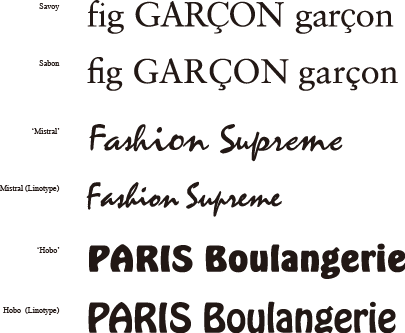
Q:「フォントの見方」について
1-1 フォントの良し悪しの見分け方
ソフトウェア等と同様、お金を払って使ってみないとフォントの実際の良し悪しはわかりませんが、何かのおまけについてくるフォント、格安フォントの中にはとんでもないものがあります。格安フォントの中から数書体みただけでもいくつか問題が見つかりました。
1列目サンプル参照:
「Savoy」という名前のついた Sabon のクローン書体です。
fi 合字がちゃんとしていないとか、小文字の g がやたらに扁平だとかは細かく見ると気になりますが、それよりも致命的なのはアクセント付き文字にまったく別のデザインの文字が混じっていることです。この場合は大文字 C の下にフランス語のシディラのアクセントが付いた文字は別の書体のデザインです。
今の時代、ロゴなどにフランス語の単語を使う可能性は十分あります。あなたがクライアントなら、こんなデザインに料金を払いますか? 怪しげな名前の格安フォントには、こんなとんでもない文字がどこに潜んでいるかわかりません。
ちなみに下はライノタイプから出ている由緒正しい Sabon のデジタル版です。
3列目サンプル参照:
堂々と「Mistral」という名前がついているのですが、オリジナルの活字書体に忠実なライノタイプ社の Mistral と比べると違いは歴然です。上の「Mistral」は本の付録についていました。字の形はいいかげんで、小文字のつながりがうまくいっていません。
5列目サンプル参照:
オリジナルの活字書体 Hobo は、小文字を混ぜて組んでも単語のデコボコが少なくなるような小文字 g や p などのディセンダーをベースラインに収めたり x ハイトを極端に高くしたりと工夫されていて、独特の雰囲気を持つアールヌーボー風の見出し用書体です。上が本の付録の「Hobo」です。小文字のディセンダーをベースラインに収めるというコンセプトは無視されていますし、大文字のスペーシングは良くありません。下がライノタイプの Hobo です。
フォントはちゃんとしたメーカーから買ったほうが結局は安くつくはずです。
1-2 吟味の仕方:フォント検索ツールを活用しよう
「テーマにあった雰囲気の書体」「適材適所の書体」を選ぶことは大事です。とくに欧米のデザイナーは自分の手持ちのフォントにテーマに合うものがないと、フォントメーカーに「こういう雰囲気のものがないか」と問い合わせをしてくるくらい神経を使います。
ライノタイプのホームページでは、ウェブサイトでの試し組みやグリフの一覧を見ることができます。とくにロゴなどでの見え方がどうなのか気にされる人も多いと思うので、購入の前にフォントの吟味ができるようにウェブサイトを活用してはどうでしょう。買ってから「まさか大文字の R がこんな形だったなんて」などと後悔しないように、組む単語が決まっている場合はグリフのデザインや単語にしたときの字並びを確認してから買いましょう。